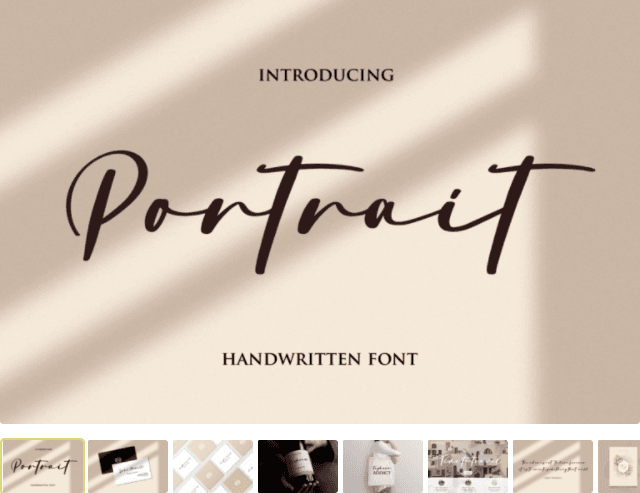
Portrait – Handwritten Font
Портрет - современный рукописный шрифт. Этот шрифт выполнен в современном стиле, очень повседневный и подходит для различных дизайнерских нужд. он идеально подходит для логотипов, брендов, заголовков, сообщений в социальных сетях, рекламы, упаковки продуктов, дизайна продуктов, этикеток, фотографий, водяных знаков, специальных мероприятий, журналов, веб-дизайна и т. д.